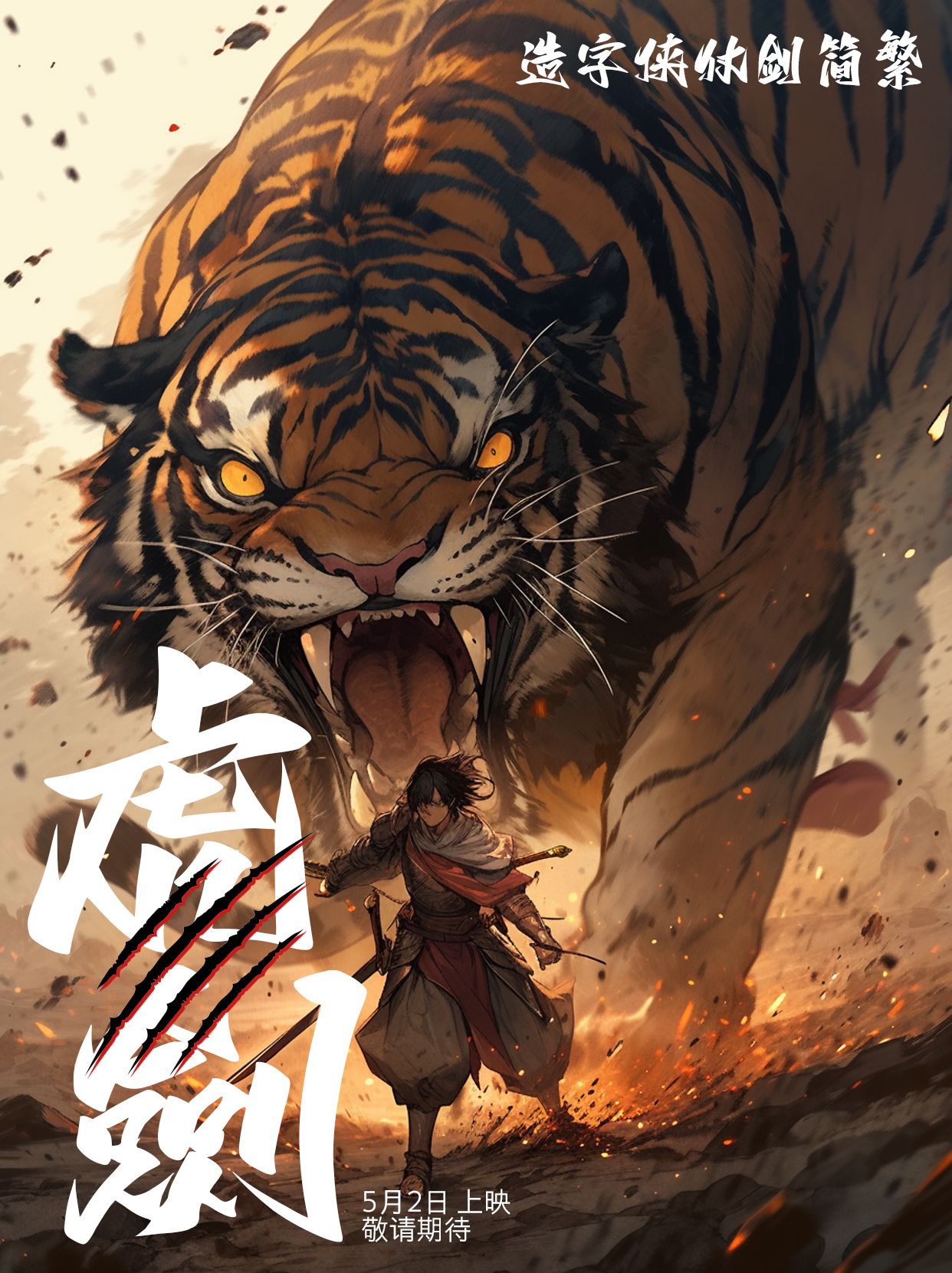
仗剑汉字武林 | 造字侠仗剑简繁,一款剑气纵横,潇洒豪气的书法字体
武侠是中国人心中的超级英雄史诗,每一个人心中都有一个仗剑江湖、行侠除恶的英雄。今天励字战士跟大家分享一款剑气纵横,潇洒豪气的书法字体——造字侠仗剑简繁。
字形稳重、笔画张扬的书法字体。折、提、钩等部首干净利落、高度折叠,颇有豪侠仗剑江湖的潇洒之感。适用于游戏、海报、视频、封面等多种场景。